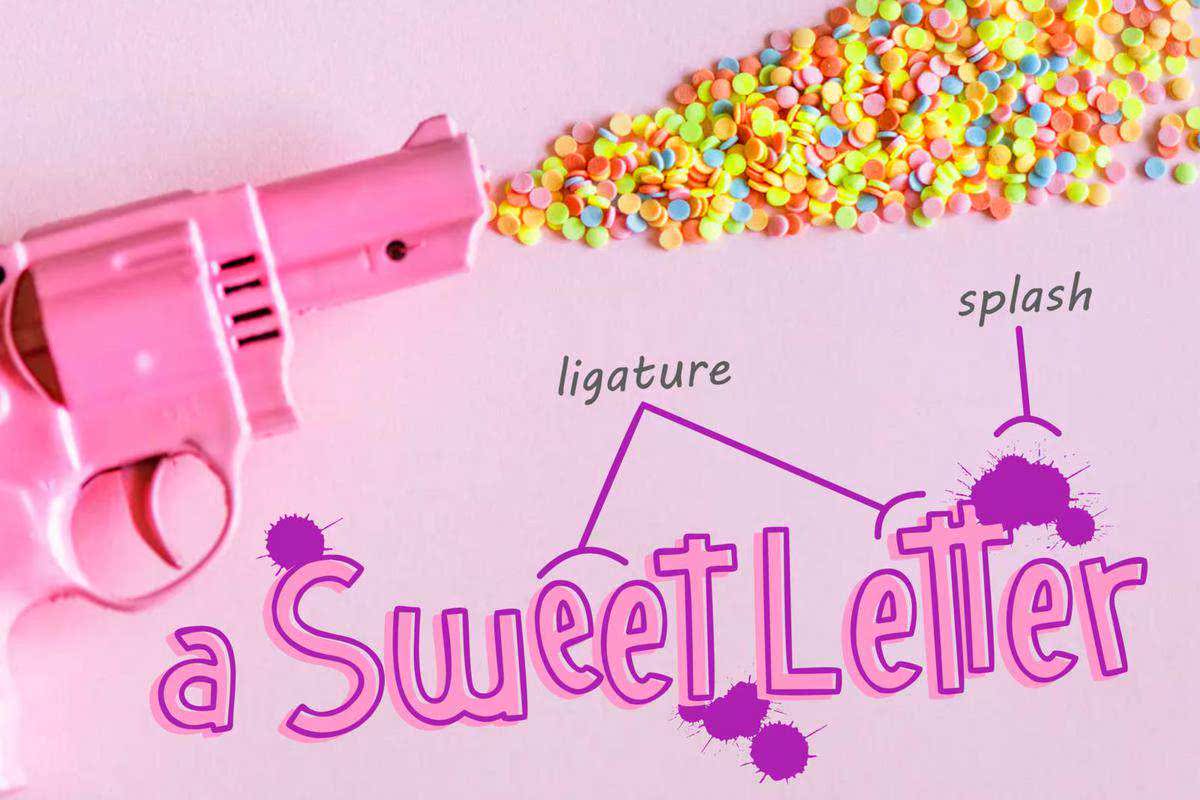
HellofReday是一款有两种风格的字体,非常有趣。由HellofReday YouTheLine和HellofReday(纯色)组成。这款字体非常适合于娱乐或儿童主题的设计项目。HellofReday字体适用于衬衫、徽标、婚礼设计、社交媒体、广告、名片、封面杂志、标签、摄影、水印、邀请函、,文具和任何需要用两种样式书写的项目。Hellofreday是一种非常有趣的两种样式。由Hellofreday和Hellofreday(实心)组成。这非常适合于以娱乐或儿童为主题的设计项目。Hellofreday字体适用于衬衫、徽标、婚礼设计、社交媒体、广告、,名片、封面杂志、标签、照片、水印、邀请函、文具和任何需要用两种样式书写的项目。